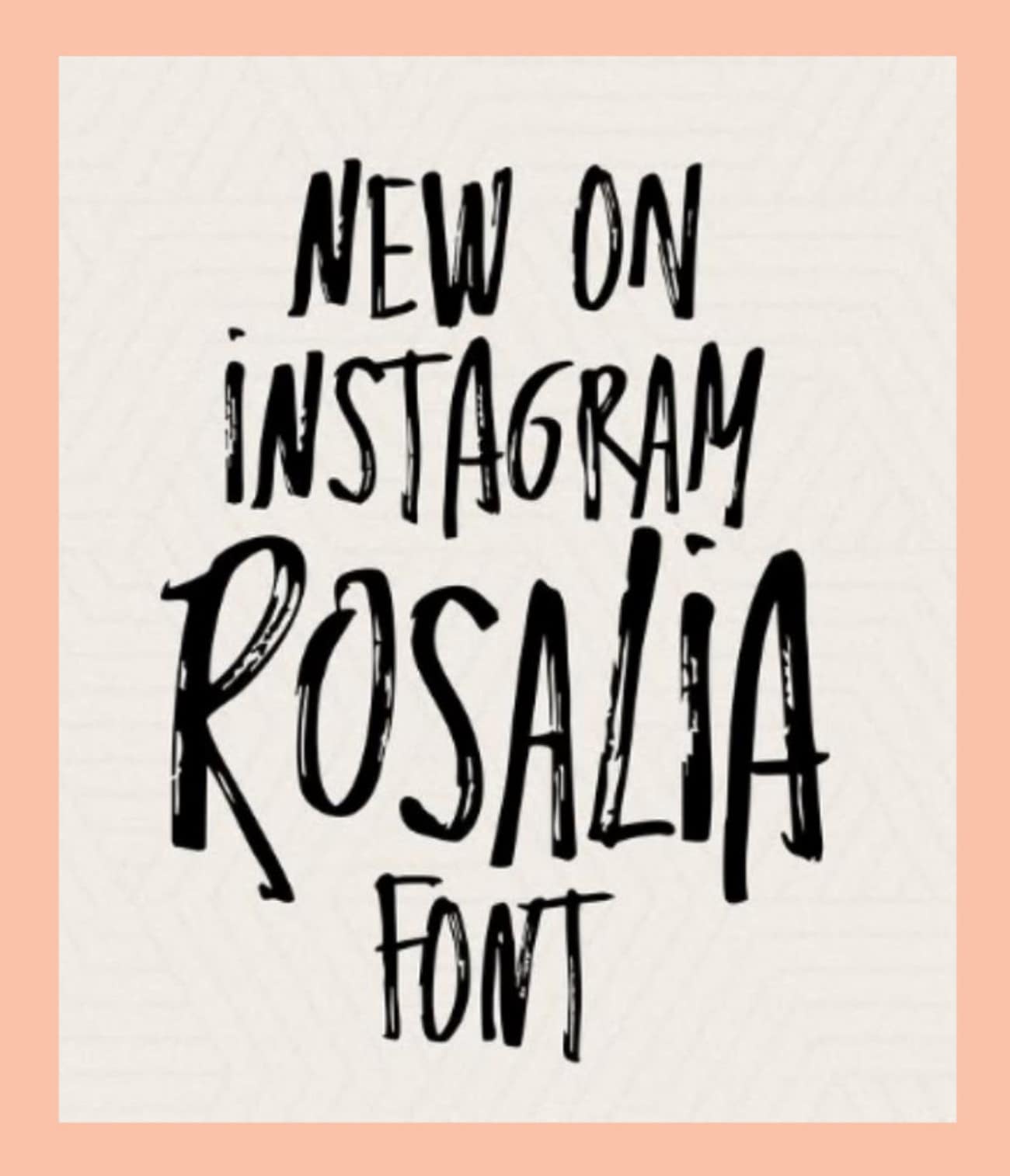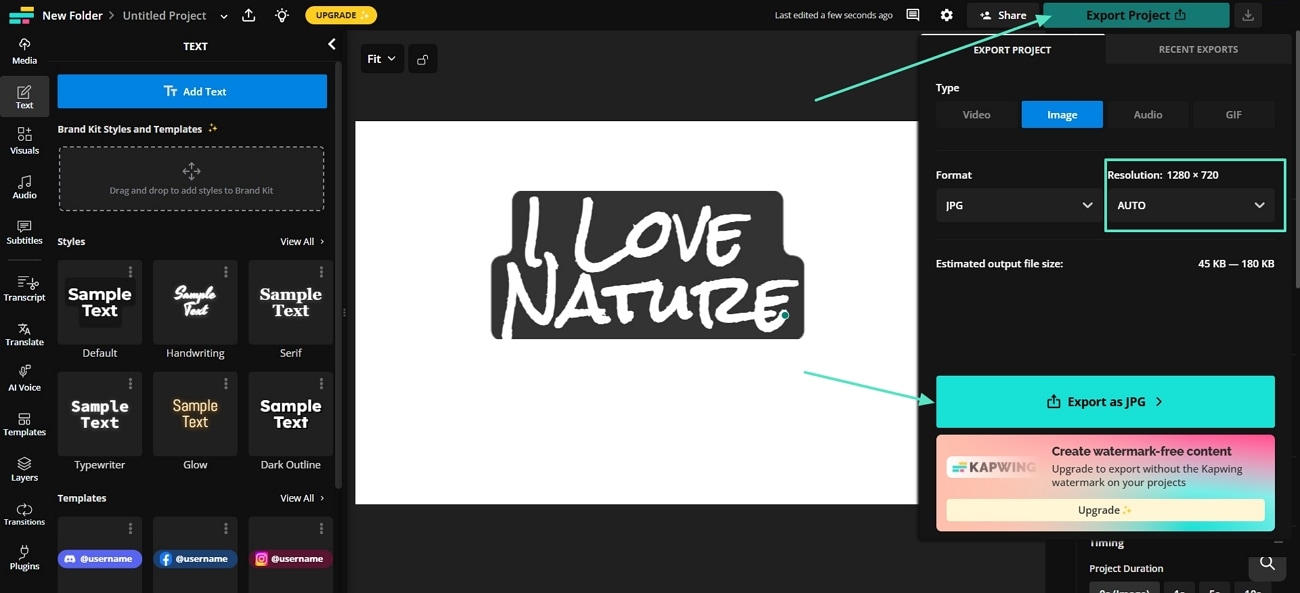
O Instagram da fonte Rosalia é um dos estilos mais empolgantes lançados para o aplicativo. Lançada mundialmente em julho de 2025, foi fruto de uma colaboração criativa com a popstar espanhola Rosalía. A fonte é ousada, manuscrita e cheia de energia, dando até mesmo a um story ou reel um toque pessoal. Com sua textura bagunçada, traçada, semelhante à tinta e rabiscos escondidos, transmite um ar divertido e descontraído.
Parte 1. O que é a fonte Rosalía?
Imagine querer que seus stories ou reels pareçam mais pessoais, quase como uma letra feita à mão no papel. É aí que a fonte Rosalia do Instagram se destaca, com letras ousadas, desajeitadas, todas em caixa alta, que parecem expressivas e autênticas. Os traços semelhantes à tinta e as formas irregulares dão um ar natural e artesanal à fonte. É mais do que texto; é uma identidade criativa. Ao usá-la, você transmite energia, paixão e individualidade.
Além disso, essa fonte traz surpresas escondidas, como ao digitar símbolos como <3 or *** that can unlock hand-drawn doodles of hearts and stars. Co-designed with Rosalia, this limited-time style brings culture, emotion, and personality to Instagram posts.
Suponha que você está compartilhando um reel ou um story e queira que ele pareça diferente, não comum. As fontes normais simplesmente não capturam o clima nem combinam com seu estilo. É aí que a fonte Rosalia faz a diferença com seu visual ousado, manuscrito, e imediatamente dá personalidade à sua postagem. Se você quer usar a fonte Rosalia para se destacar no Instagram, siga os passos abaixo:
Os stories são onde as pessoas compartilham momentos do dia a dia, e se destacar aqui faz toda a diferença. As fontes são essenciais para tornar os stories atraentes, e a fonte Rosalia Instagram tornou-se a escolha preferida para atualizações criativas.
Agora, imagine adicionar ainda mais estilo com os rabiscos escondidos da Rosalia, que serão um toque criativo para o seu story. Digite :-) e um emoji sorridente brincalhão aparece, ou use <3 to create a hand-drawn heart. To know how to create one, you should do the following steps:
Parte 4. Crie sua própria fonte Rosalía personalizada para o Instagram
Se você está procurando como obter a fonte Rosalia no Instagram, o processo é simples. Esse estilo manuscrito faz bios, legendas e postagens se destacarem com um visual ousado inspirado na Rosalia. Vamos conhecer algumas ferramentas e um guia detalhado para ajudar você a criar sua própria fonte Rosalía personalizada para o Instagram:
Conclusão
Este artigo abordou as etapas detalhadas sobre como obter a fonte Rosalia no Instagram, com diferentes ferramentas usadas para gerar fontes personalizadas. A fonte Rosalia se tornou uma forma de expressar criatividade nos stories, reels, legendas e bios do Instagram. Como bônus, também exploramos uma ferramenta de edição de vídeo, o Filmora, que você pode usar para adicionar fontes Rosalia aos seus vídeos do Instagram, juntamente com recursos avançados de edição.